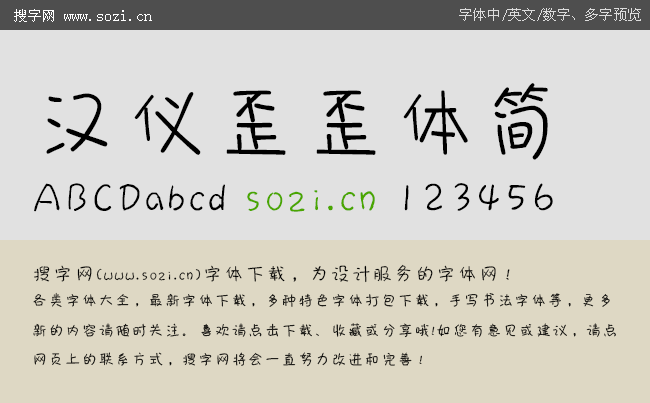
漢儀歪歪體簡(jiǎn)手機(jī)字體包
搜字網(wǎng)給大家提供一款漢儀歪歪體簡(jiǎn)手機(jī)字體包手機(jī)中文字體下載。這款手機(jī)字體是一款兒童手寫(xiě)風(fēng)格的藝術(shù)字體,字體筆畫(huà)帶有稚氣,活潑可愛(ài),非常具有趣味性。整體效果十分出色。喜歡的朋友趕快下載吧。